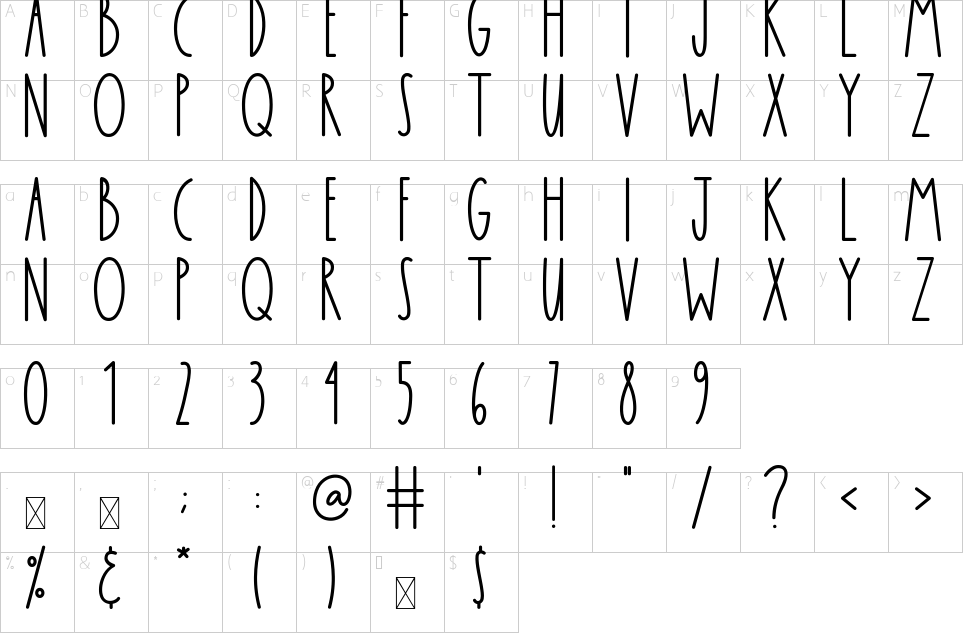
Descubra a bela Minimalist Farmhouse font, perfeita para aqueles que adoram um estilo minimalista e casavilha no seu design. Desenvolvida pela equipe da jimtype studio, esta fonte foi projetada para oferecer um visual limpo e confortável, perfeito para projetos de design gráfico que valorizam simplicidade e conforto. Com seu design elegante e moderno, você pode escolher entre um letraset minimalista ou com traços mais realistas, dependendo de seu projeto. E, como uma fonte gratuita, 1001 Free Fonts oferece uma variedade imensa de opções para escolher a que melhor se encaixa em seu projeto. Com Minimalist Farmhouse, você pode dar um toque único e confortável a seus projetos, seja em sua identidade visual, em texturas ou em qualquer outro tipo de design. Descubra agora, e encontre a fonte perfeita para seu próximo projeto.